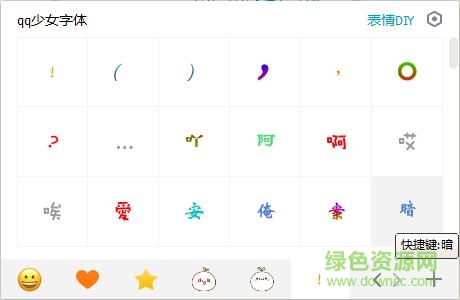
软件介绍 软件标签: 少女QQ字体 QQ字体 少女qq字体是由绿色资源网小编为大家提供的一套免费字体工具。这款字体一共包含了887种可爱的字体,非常适合少女心较强的朋友们安装使用。喜欢的小伙伴快来拿走吧!字体介绍可爱的美少女qq字体为大家提供了多种色彩绚丽形状优美的QQ字体,只要本QQ字体包中包含的文字都可以再聊天过程中一输入普通汉字的方法输入,本QQ字体包采用了EIP的文件格式,只要你安装了QQ2005及以上版本只需要双击就可以进行安装。字体特点呆萌可爱;支持多种运行环境; 软件截图 上一张下一张(1 / 1) 安装详细截图 猜你喜欢 可爱字体 qq字体 可爱字体 可爱字体一般都以卡通、秀气、柔美、女性、儿童等为主调,之前有很多网友都在寻找可爱的字体有哪些?今天由绿色资源网小编为大家分享数十款可爱中文字体打包下载,每款字体都有其可爱之处,感兴趣的朋友欢迎来绿色资源网下载体验! 查看更多>> 脚印星星可爱字体 10.74M/中文/10.0/下载 汉仪pp体简 1.70M/中文/5.0/ttf版下载 汉仪黛玉体简 2.77M/中文/10.0/免费版下载 汉仪晨妹子 5.55M/中文/7.5/简体免费版下载 可爱心形字体 6.39M/中文/3.6/免费版下载 天使萌猫字体 8.66M/中文/8.5/下载 qq字体 qq字体是qq聊天当中一种特殊的字体,这些字体风格各异,酷炫的、可爱的、跳动的各式各样,让你在聊天当中别具一格,告别qq默认的字体,这里提供了qq字体下载大全和一些qq字体包,大家可以看一看。 查看更多>> QQ字体修改器 0KB/中文/5.0/v5.6 安卓版下载 qq字体管家app 2.03M/中文/5.0/v1.1 安卓免费版下载 QQ字体汉仪仙侠体 5.15M/中文/2.5/下载 方正刹那永恒字体 376KB/中文/5.0/下载 初恋微酸简字体 1.70M/中文/5.0/下载 qq半岛未凉字体 1.70M/中文/3.3/下载 其他版本下载 标题 大小 更新日期 下载 下载地址 电脑版 可爱的美少女QQ字体 共887款 点击报错 软件无法下载或下载后无法使用,请点击报错,谢谢! 关闭报错反馈 请描述您所遇到的错误,我们将尽快予以修正,谢谢! *必填项,请输入内容 本类最新 五彩缤纷的qq聊天字体 全新的qq字体 全套漂亮可爱的QQ彩色字体打包 粤语QQ字体 免费版 15款漂亮的QQ字体 qq阴影文字 相关文章 不用QQ用什么聊天?替代腾讯QQ的聊天工具推荐 qqexternal.exe是什么进程? 怎样解决电脑可以登QQ不能上网的问题 系统日期错误导致无法安装QQ、播放器等常用软件维修一例 iPhone和iPad的QQ邮箱设置教程 WindowsXP系统QQ语音聊天时对方听不到使用者的声音故障解决方案 用户评论 热门评论 最新评论 发表评论 查看所有评论(0) 昵称: 请不要评论无意义或脏话,我们所有评论会有人工审核. 字数: 0/500 (您的评论需要经过审核才能显示)